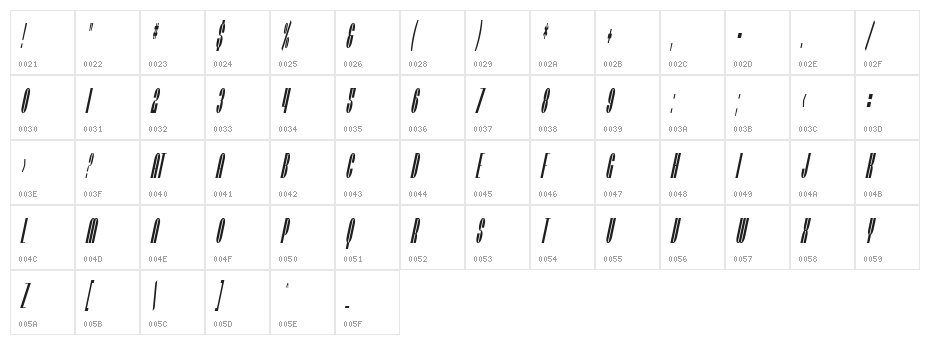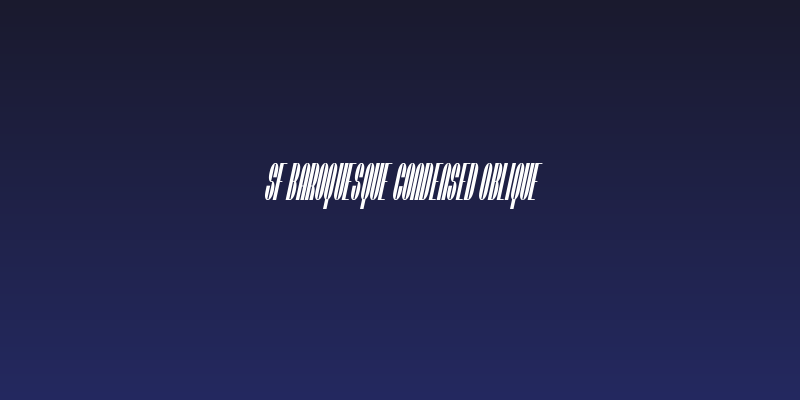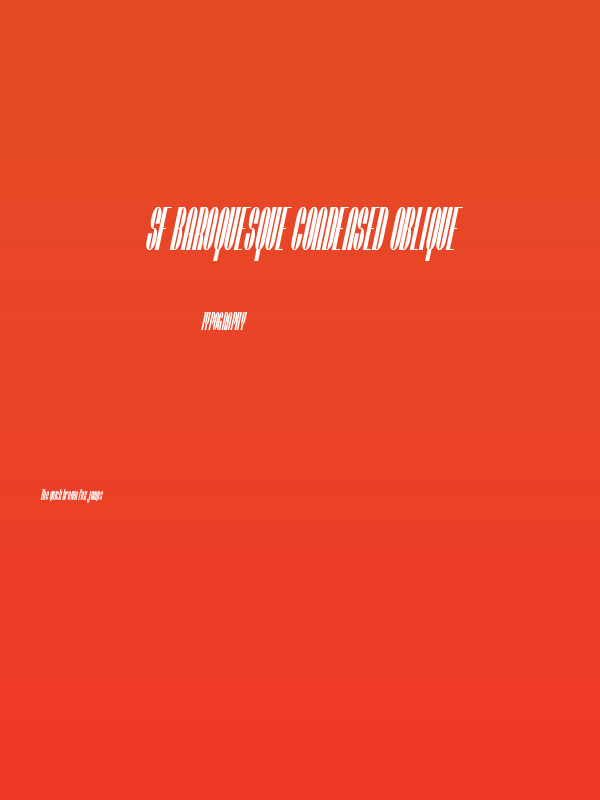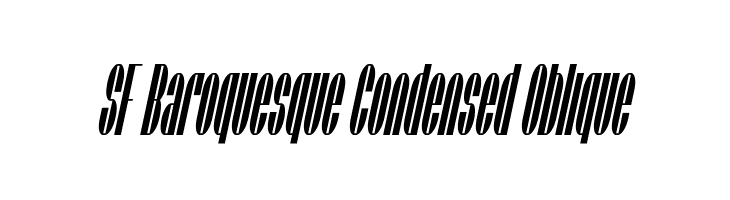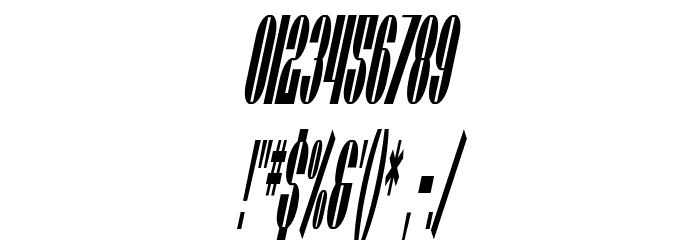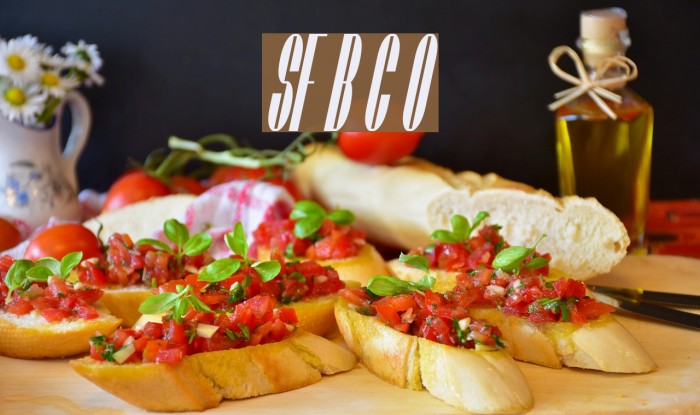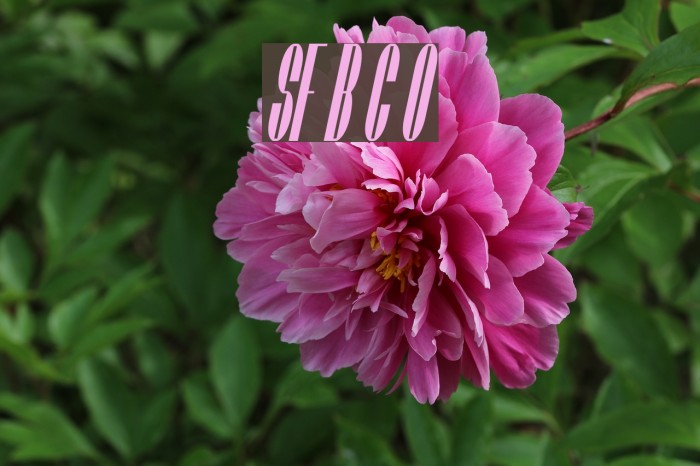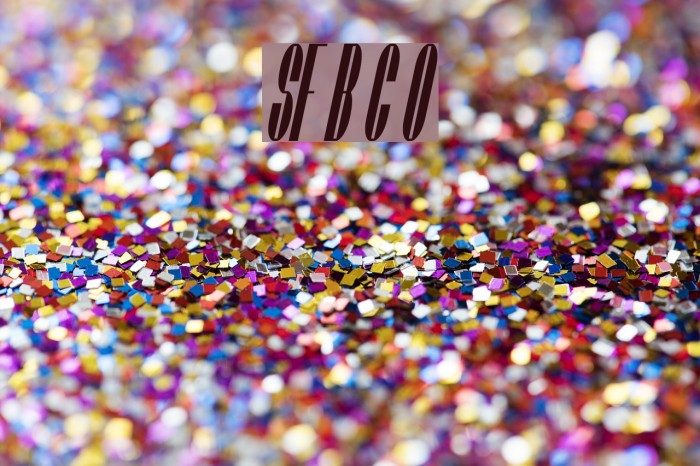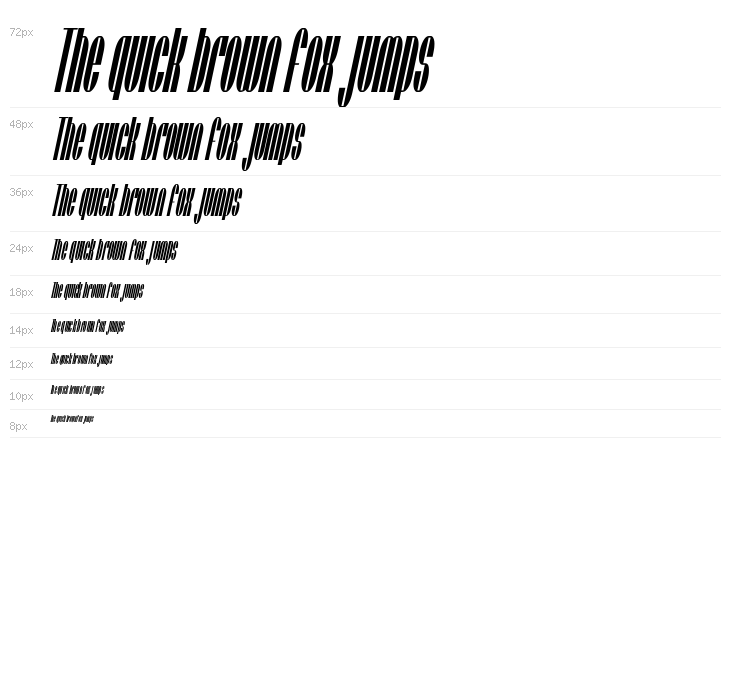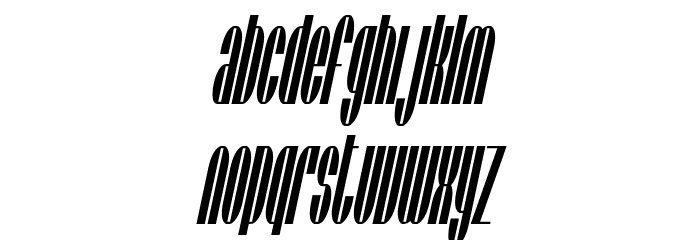
SF Baroquesque Condensed Oblique Font
| Vorgeschlagene Projekte | Ideal for use in advertising, posters, and branding where a strong visual impact is desired. |
SF Baroquesque Condensed Oblique